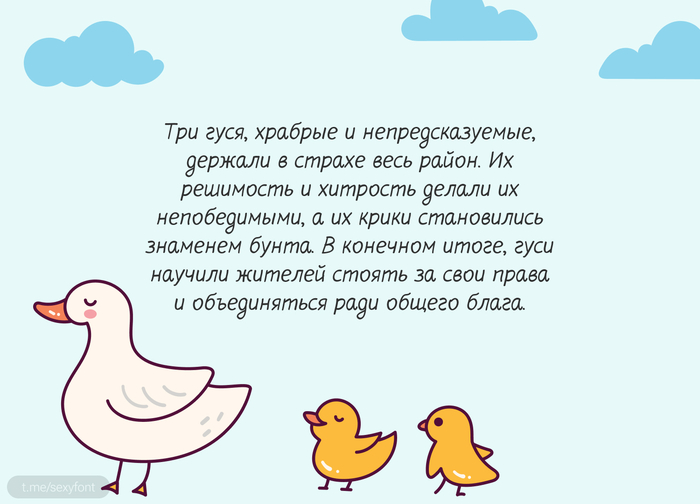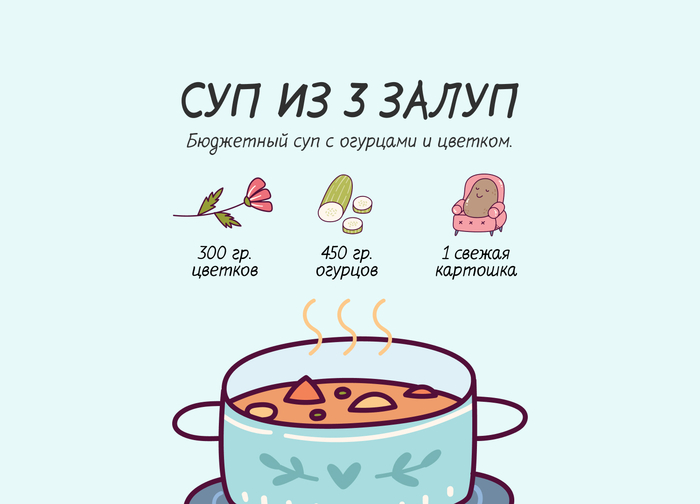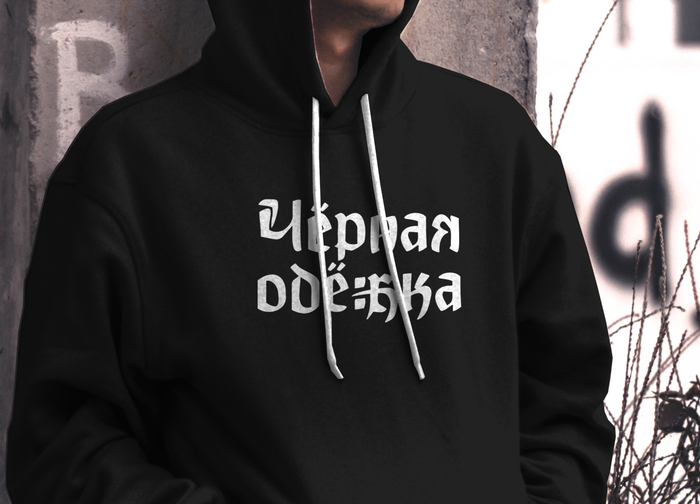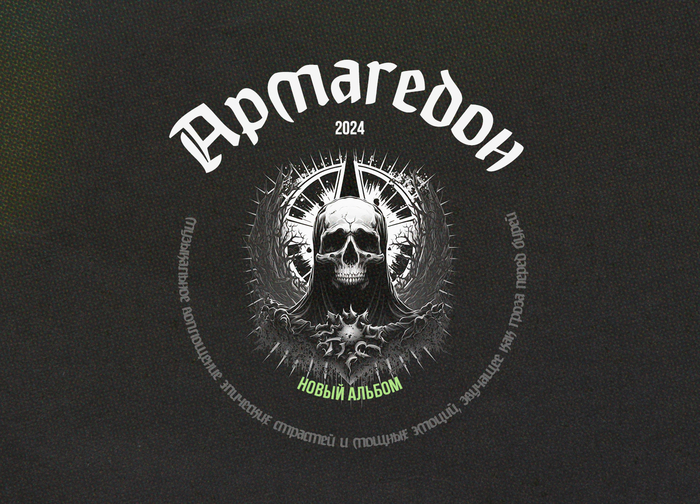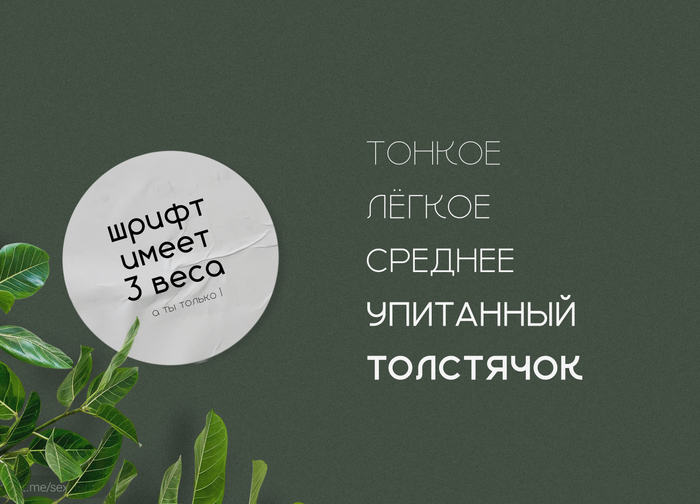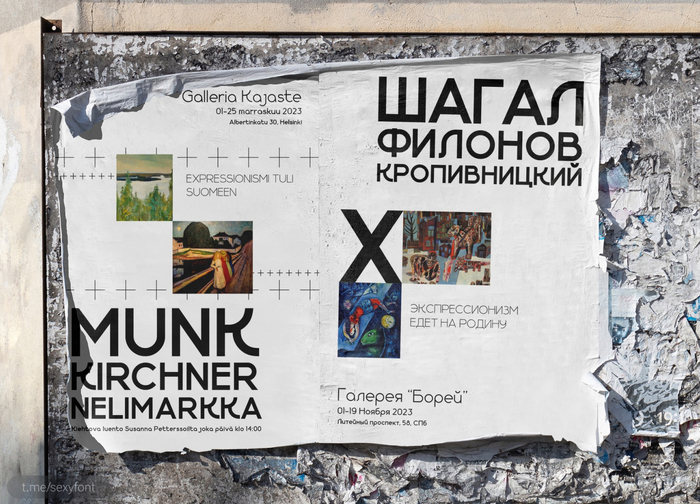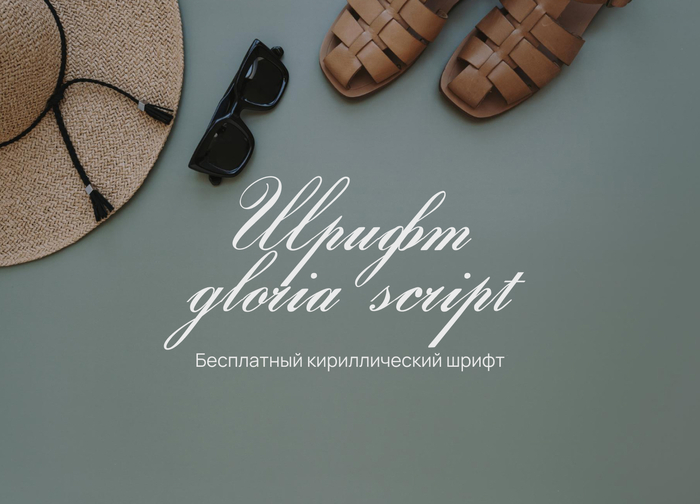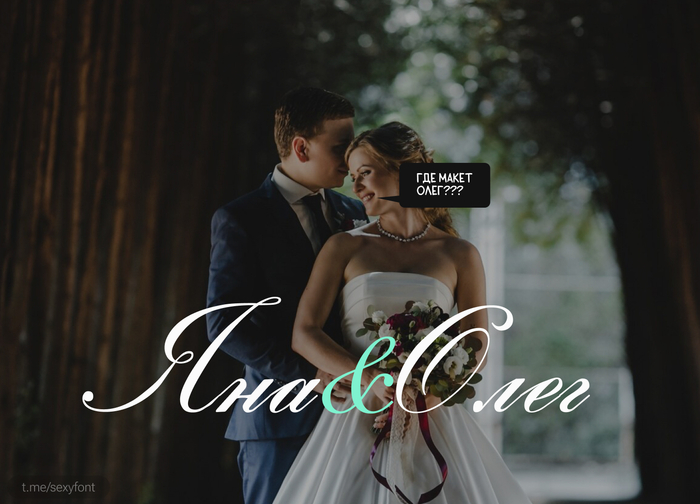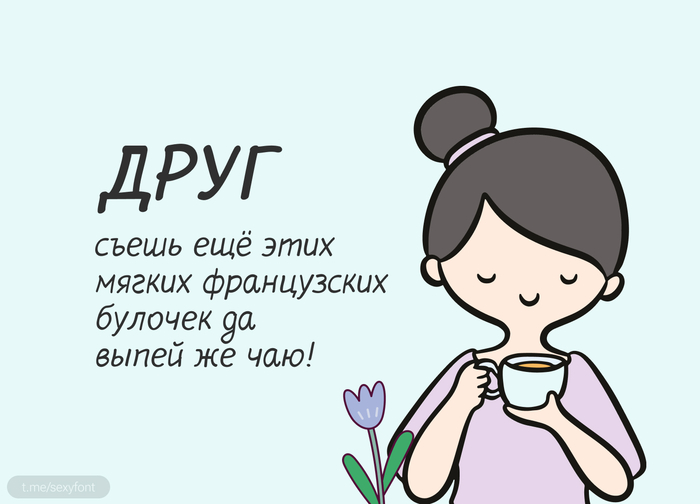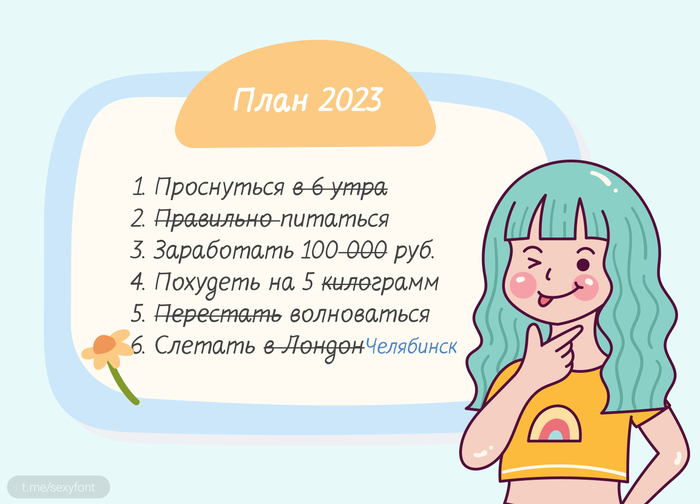
Шрифт Gloria Script
Элегантный курсивный шрифт Gloria Script идеально подходит для оформления приглашений, открыток и т.д Автор кириллизации: Alexandra Gophmann. Условия использования: кирилизация бесплатна для личного и коммерческого.
Riviera. Шрифт РИВЬЕРА легкий и теплый, подвижный и пластичный, вдохновленный летним побережьем и гедонизмом. Акцентный, контрастный и плавный. Включает кириллицу и латиницу.
Шрифт cruinn. Бесплатный, читаемый шрифт с поддержкой кириллицы.
Calama. Привет) лови презентацию. В копилку компактных и естественно кириллических шрифтов. (По другому тут не бывает)
Archip. Оч. мне нравится этот с виду простой шрифт. Но есть в нем что-то. Как минимум он декоративный, но без чрезмерных финтифлюшек, что не губит его читаемость. Много где можно использовать.
BrahmsGotischCyr. Шрифт для любителей готики и мистики. Идеально для рекламы твоего замка. Верное ударение поставишь сам. Специфичный, не оч. читаемый. Но пригодится. Сохраняй. Иначе вампиры обидятся.
Мощный, тяжёлый шрифт Molot. Сделал такую вот презентацию белочки с орешком. Уверен ты найдешь ему применение.
Привет друзья) Доделал новую презентацию. Шрифт Flow. Кириллический рукописный. Идеально для создания заметок)